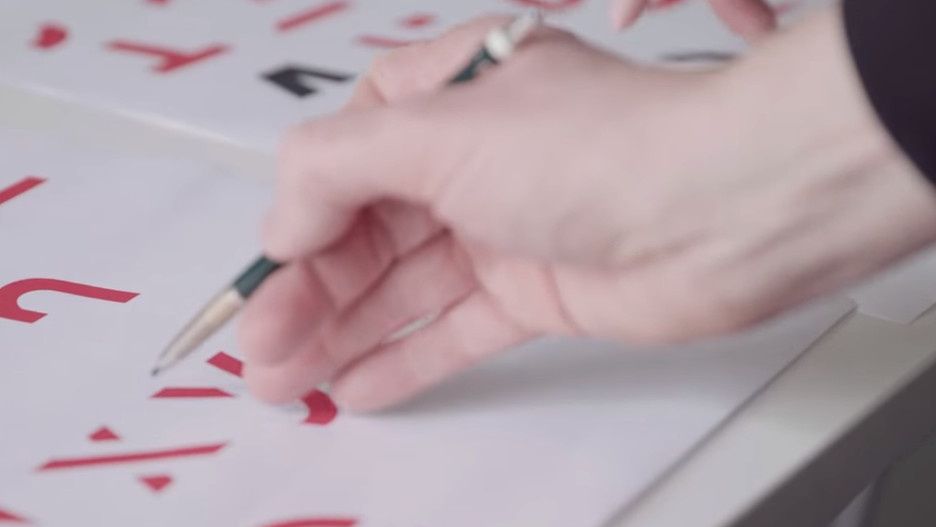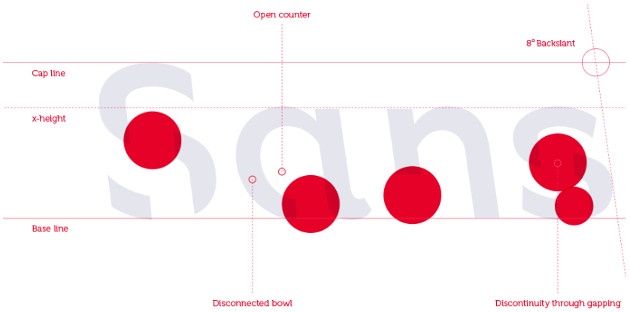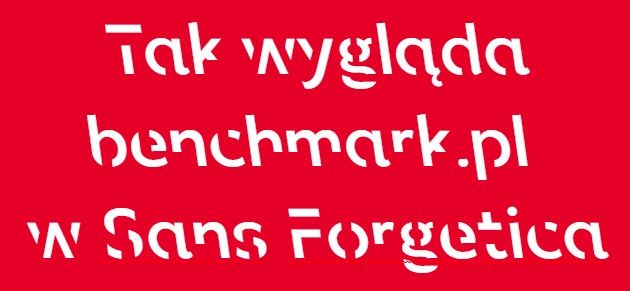
Chcesz wreszcie pamiętać to, co czytasz? Sans Forgetica jest dla ciebie
Sans Forgetica to font stworzony dla osób, które mają trudności z zapamiętywaniem tego, co czytają. Można go pobrać zupełnie za darmo i zainstalować w systemie lub od razu w Google Chrome.
Internet to niewyczerpane źródło informacji – problem w tym, że większości z nich nie zapamiętujemy. Naukowcy twierdzą, że wśród powodów, dla których tak się dzieje, znajduje się przyzwyczajenie wzroku do typowego fontu. I tak zrodził się pomysł na Sans Forgetica.
Sans Forgetica to nowy font stworzony w taki sposób, by pomagać ludziom zapamiętać to, co przeczytali. Zapisane nim słowa są nieco trudniejsze do przeczytania, co ma powodować większe skupienie na treści, a przez to – zwiększyć szanse na jej zapamiętanie. Aby to osiągnąć, autorzy przekrzywili znaki (w przeciwnym kierunku do typowej kursywy) i wycięli ich fragmenty.
Sans Forgetica specyfikacja
Mając na uwadze swój cel naukowcy z RMIT University stworzyli wiele różnych fontów, a następnie przeprowadzili serię eksperymentów wśród uczniów-ochotników. Jak się pewnie domyślacie, najwięcej zapamiętali oni z tekstu zapisanego właśnie krojem Sans Forgetica.
Sans Forgetica BMK